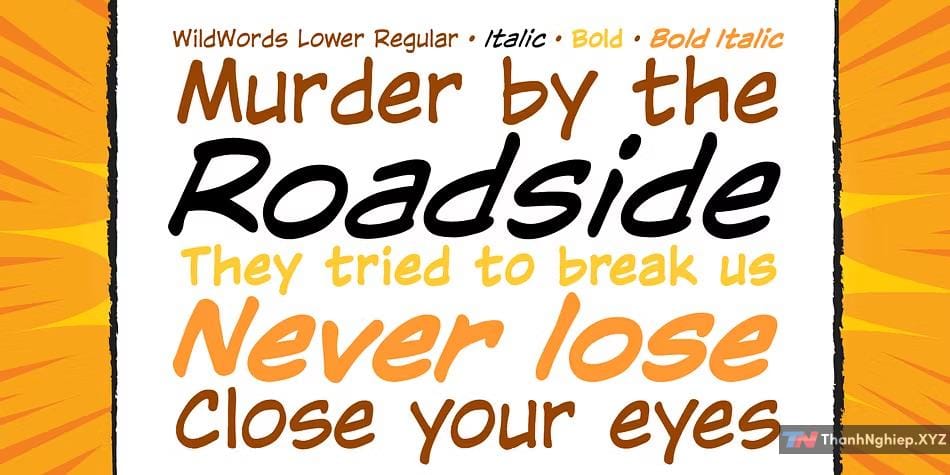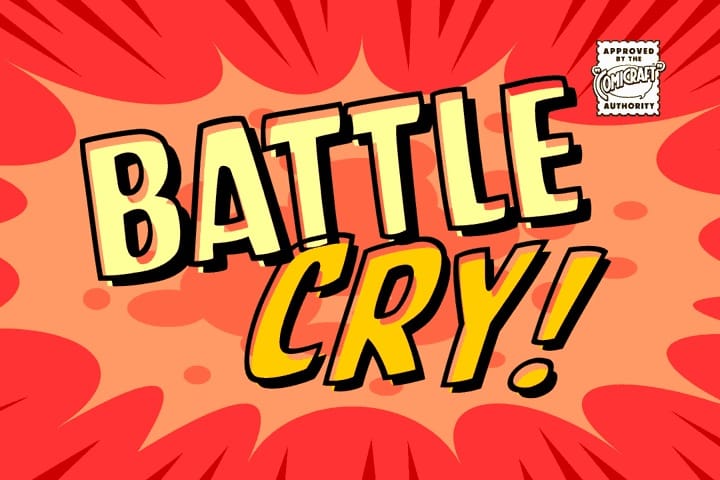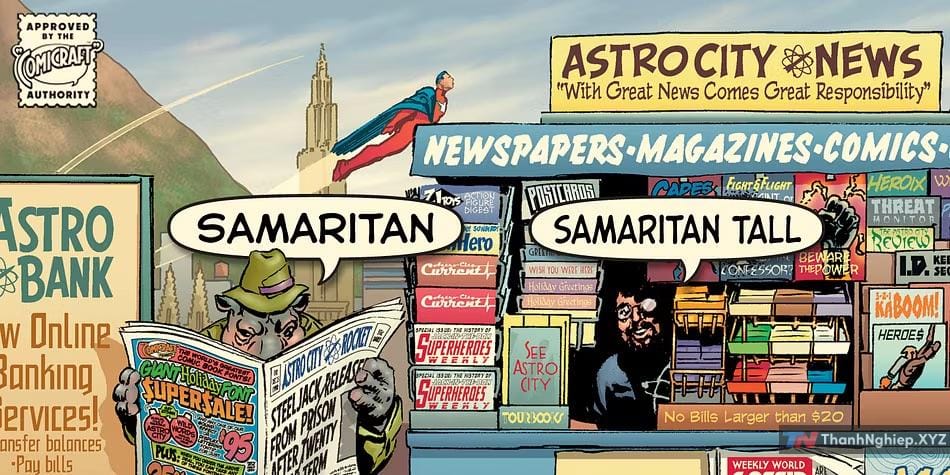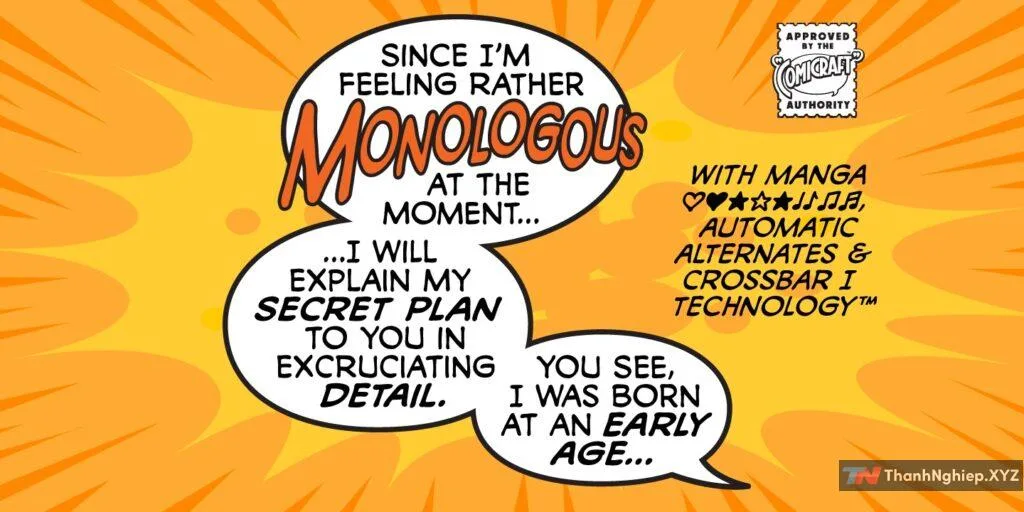
Bạn đã sẵn sàng bước vào thế giới truyện tranh đầy màu sắc chưa? Hãy để Wonderland Team dẫn lối bằng bộ 77 font việt hóa siêu cấp đắng yêu “TeddyBear” – bạn đồng hành lý tưởng cho các dự án truyện tranh, minh hoạ, poster và thậm chí là ghi chú lẫn đầy tinh nghịch trong đời sống hàng ngày!
Điểm nổi bật của TeddyBear
Đầy đủ tính năng việt hóa:
Các font trong bộ TeddyBear đã được việt hóa hoàn toàn, hỗ trợ đầy đủ dấu sắc, giù giông ngân hày nhỉ nháy. Viết tên bạn, tên người thương, hay các âm thanh “đùng đoàng” trong truyện tranh đều đầy tính nghệ.
Phong cách đa dạng:
Từ ngộ nghĩnh, dễ thương đến phong trầm ngầu, mạnh mẽ đầy cá tính – bạn sẽ không bao giờ bị nhàm chán. Mỗi font đều có tính “truyện tranh hóa” cao, đem lại động lực cho trang truyện của bạn.
Dùng cho đủ mọi nhu cầu:
Có phải bạn đang làm truyện tranh? Hay chỉ đơn giản muốn tạo một bảng chữ siêu ngộ nghĩnh cho sinh nhật người yêu? TeddyBear đã chuẩn bị sẵn, chờ bạn gán ghép!
Sự khác biệt:
Bạn sẽ tìm thấy nhiều font trên thị trường, nhưng sự kỹ lưỡng của Wonderland Team trong việt hóa đạt đến chi tiết đến từng đường cong, dấu sắc phụ. Kết quả? Bạn nhận được một bộ font hoàn hảo và thực sự “bá chất”.
Bộ font TeddyBear thích hợp với ai?
Họa sĩ truyện tranh: Dễ dàng đặt lên lời thoại, âm thanh động, hay hiệu ứng mối trường.
Nhóm sáng tạo: Bạn làm infographic, thiết kế poster, hay banner đều được.
Những tâm hồn nghệ thuật “dương phố”: Muốn làm lời chúc sinh nhật hay quote đẹp cưực? Dụng ngay TeddyBear cho thật khác biệt!
Kết luận
TeddyBear không chỉ là một bộ font, đó là phong cách, là cảm hứng, và là tâm huyết. Wonderland Team cam kết mỗi chi tiết đều đầy chất xám, từng chữ là tài sản để có thể khiến bạn tự hào. Nêu bạn muốn tách biệt trong biển sáng tạo, TeddyBear đang đợi bạn!